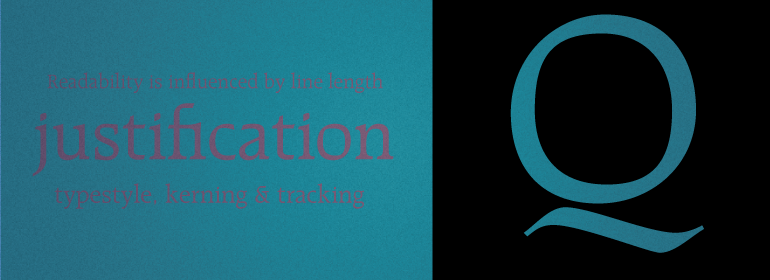
Raleigh™
Raleigh字体是基于Carl Dair最初于1967设计的字体Cartier。它是专为加拿大百年纪念活动以及1967年蒙特利尔世界博览会而设计。
Dair去世后,它被更名为Raleigh。Adrian Williams为显示家族添加了三个字重,Robert Norton设计了文本版本。
The Raleigh typestyle is based on Carl Dair's original 1967, Cartier typeface. which was designed for the Canadian Centennial and the 1967 Montreal World's Fair.
It was renamed Raleigh after Dair's death. Adrian Williams added three weights for a display series, and Robert Norton designed the text version.